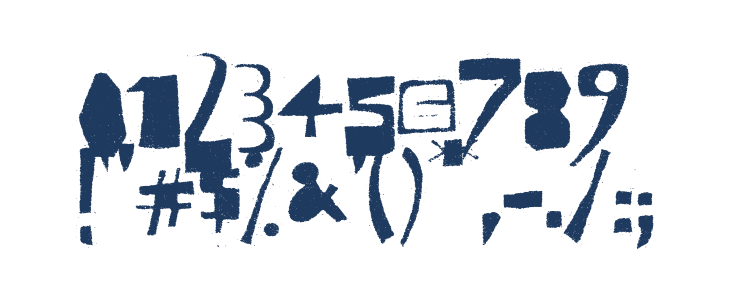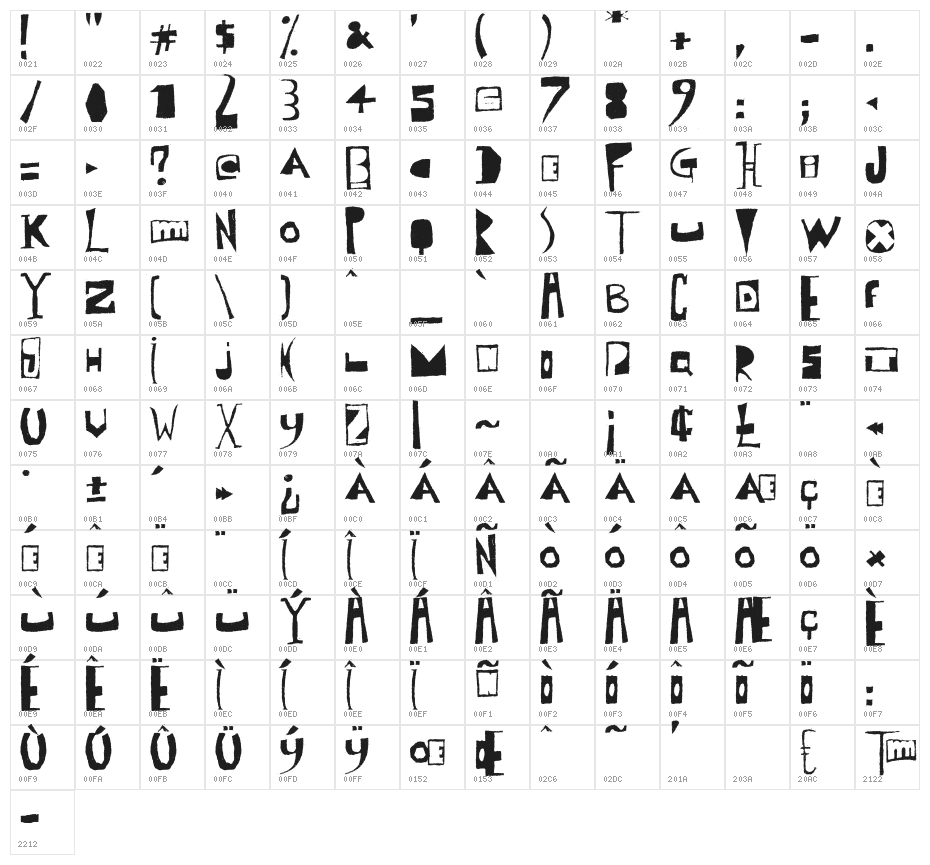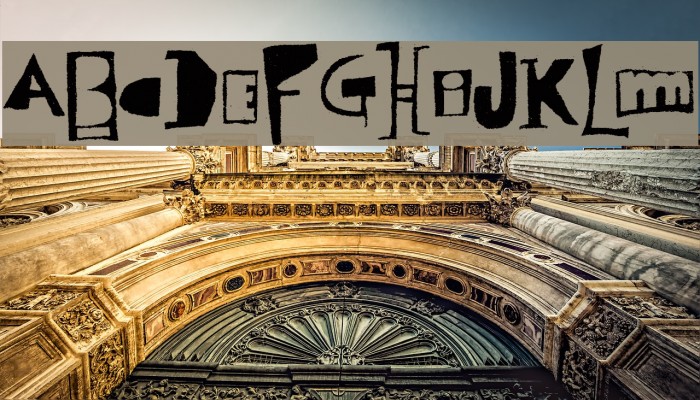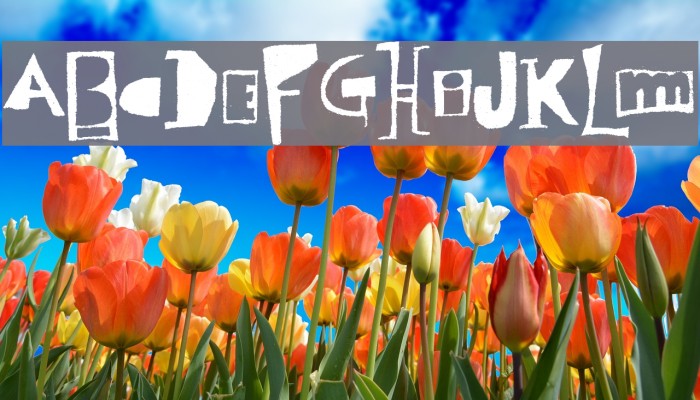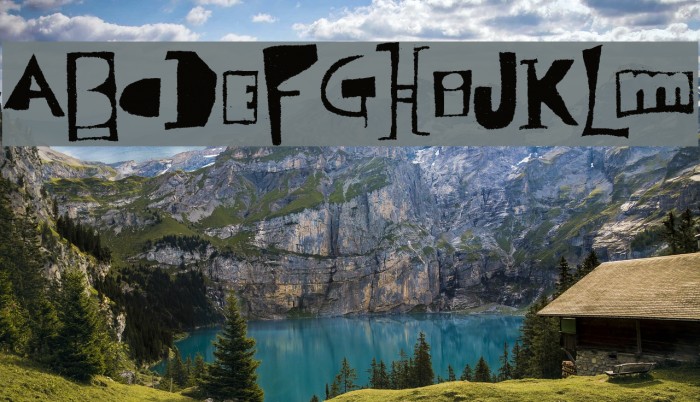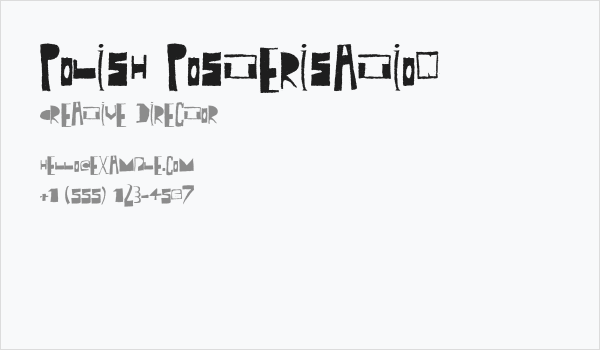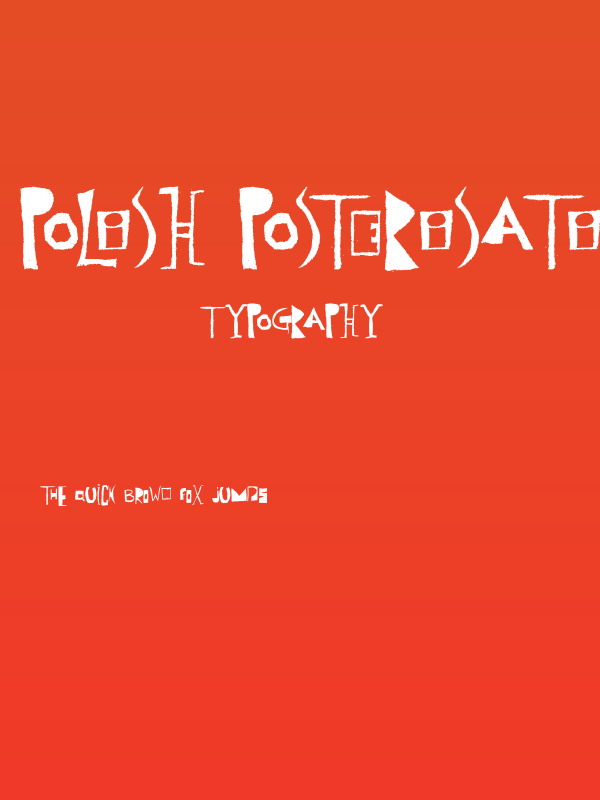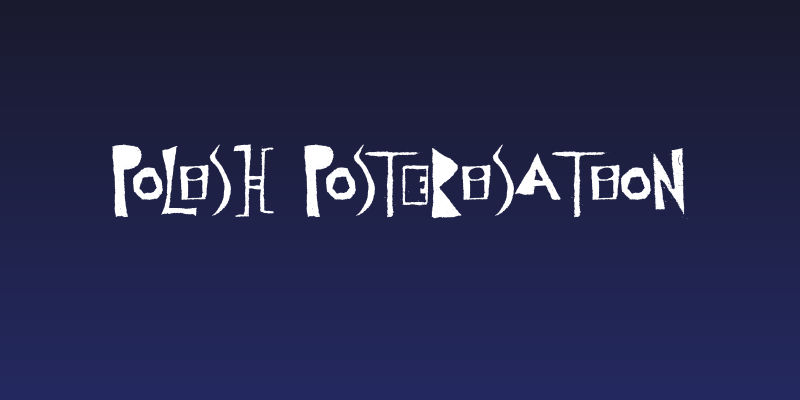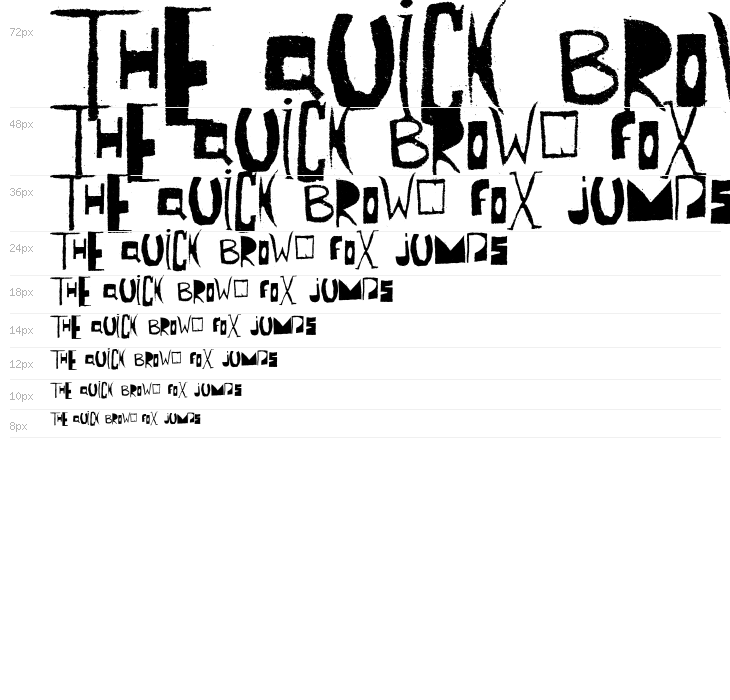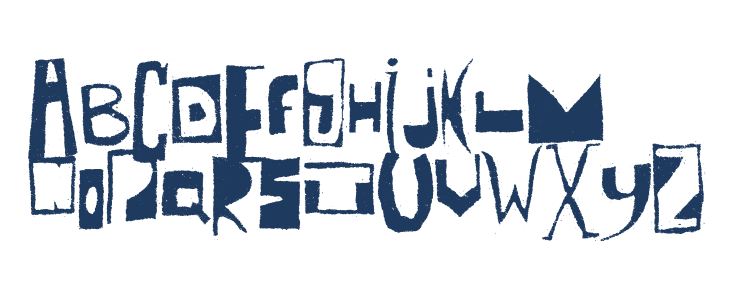
Polish Posterisation Font
| Estilo general | Artistic, Abstract |
| Caso de uso | Headlines, Posters, Artistic Displays |
| Proyectos propuestos | Ideal for posters, album covers, artistic projects, and branding that seeks a unique, expressive style. |